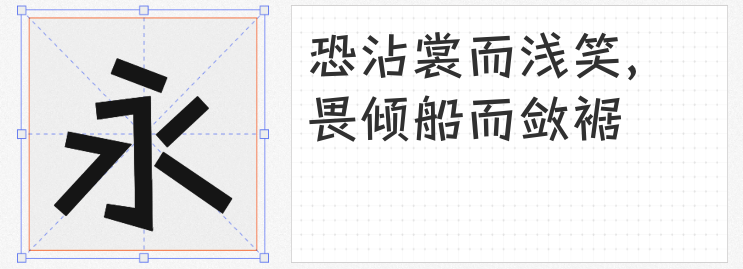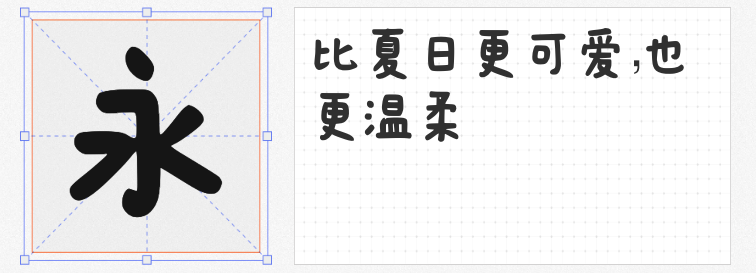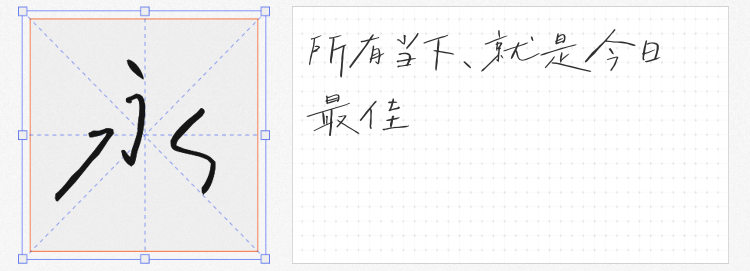
在夏日或清新主题的设计中,选对字体能让作品瞬间充满活力与氛围感。今天就为大家推荐四款风格各异且适合此类设计的免费商用字体,助你打造专属夏日的清新设计。
乡立方黑体设计灵感源于充满时代感的刷墙字体,在融合乡立方企业文化和品牌形象后,对笔形笔画、字体部件、字面空间进行了再设计。它的字形偏窄,给人一种独特的清新氛围感,仿佛将乡村的质朴与现代设计理念完美结合。在关于夏日乡村主题的设计中,如乡村旅游海报、农产品包装等,使用乡立方黑体能很好地体现乡村的清新与活力,让观众一眼就感受到夏日乡村的宁静与美好。
字体家AI造字春风由字体家AI神笔造字生成,笔画圆润灵动,卡通感十足。这种风格非常适合平面设计,比如夏日主题的插画海报、儿童产品宣传等。在设计中运用它,能为画面增添一份活泼与俏皮,让整个设计充满童趣,仿佛将观众带入了一个充满欢乐的夏日童话世界。
字制区喜脉喜欢体是一款手写字体,风格文艺、自由。它特别适合作为字数少的大标题使用,像自媒体封面标题/字幕、音乐专辑、电影海报、杂志、照片排版等场景。在夏日文艺主题的设计中,如夏日音乐节海报、旅行摄影集排版等,使用这款字体能让标题更加醒目且富有艺术感,吸引观众的注意力。
游趣体笔形像笔杆一样以直线设计,既可爱调皮,又有田园写意风格。它是基于 Fontworks 出品的日文字体扩充、调整字形而来,满足了简体中文的使用需求。在夏日田园主题的设计中,如农家乐宣传海报、田园风光摄影集等,使用游趣体能很好地体现田园的清新与自然,为设计增添一份别样的趣味。
这四款字体风格独特,各有千秋,在夏日或清新主题的设计中合理运用,定能为你的作品带来别样的魅力。